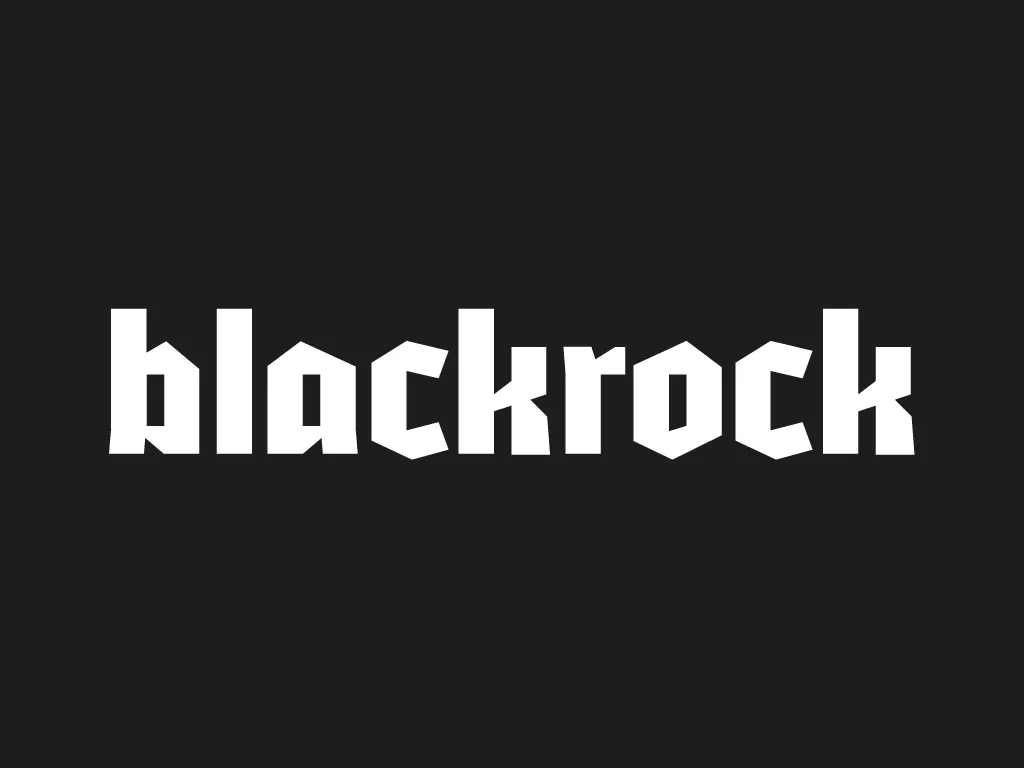
A BlackRock typeface é uma fonte de display que combina um charme vintage com uma modernidade cuidadosamente equilibrada. Inspirada por workshops de tipo blackletter, esta fonte fornece uma opção única e estilosa para usar como cabeçalho ou títulos em projetos visuais criativos. Com suas linhas grossas e textura peculiar que lembram o passado medieval do tipo, BlackRock oferece um tom robusto e poderoso. Especialmente atraente para aplicações de apresentação de slides, anúncios ou qualquer projeto onde você precisa chamar atenção. Suas nuances de design garantem uma identidade única para suas mensagens visuais. Hamilton é o designer por trás desta fonte que oferece um toque especial à sua criação.